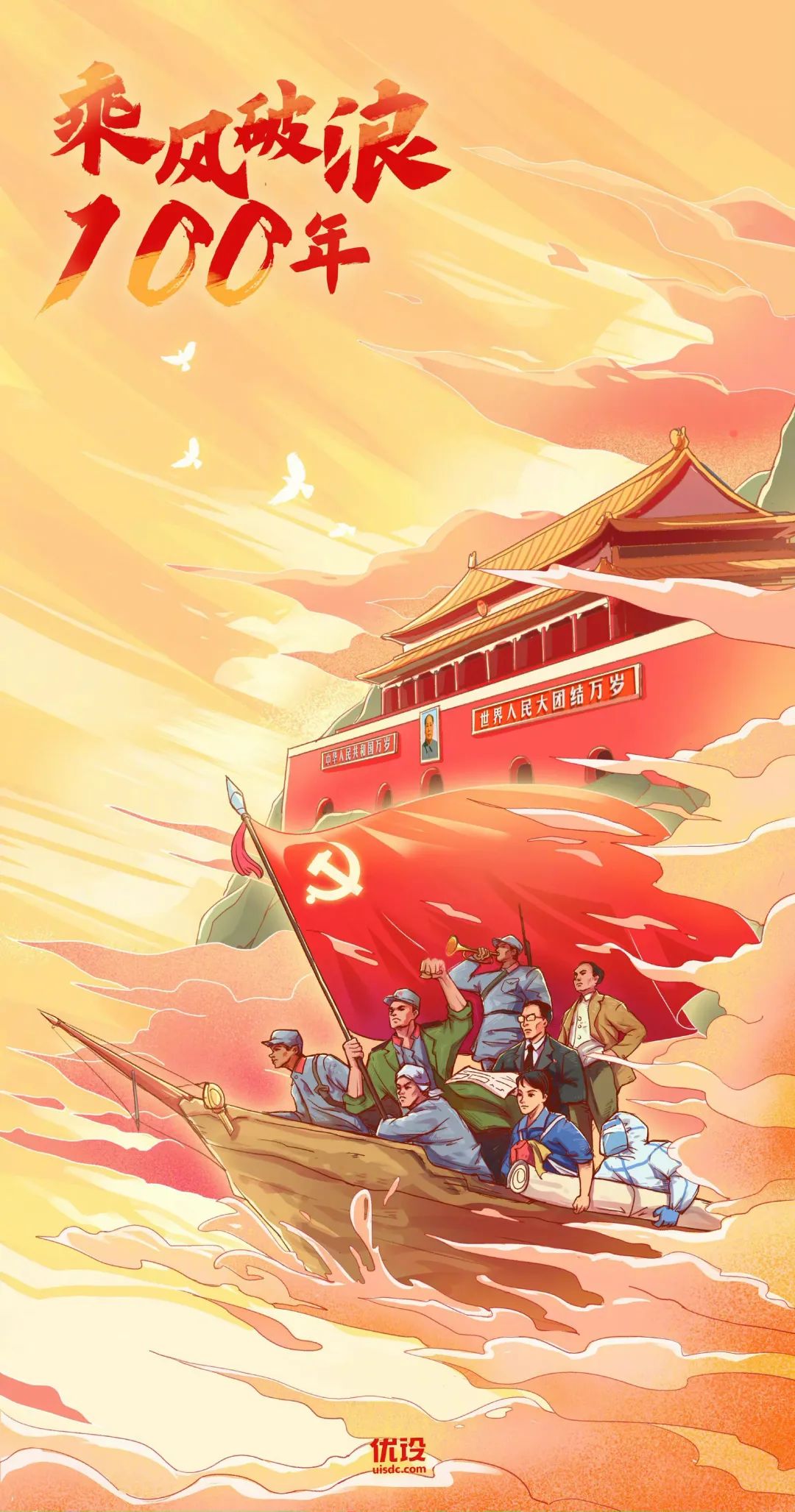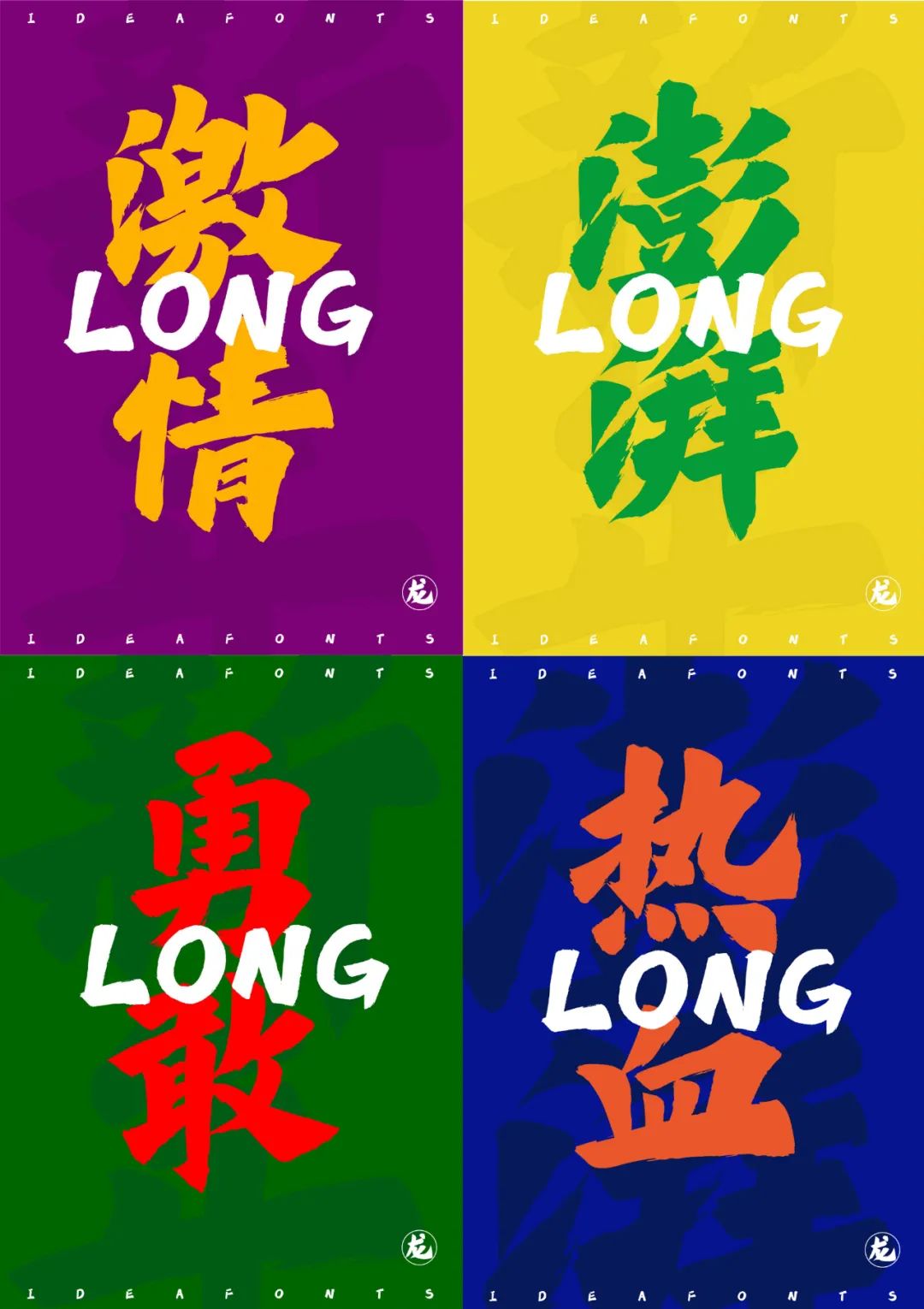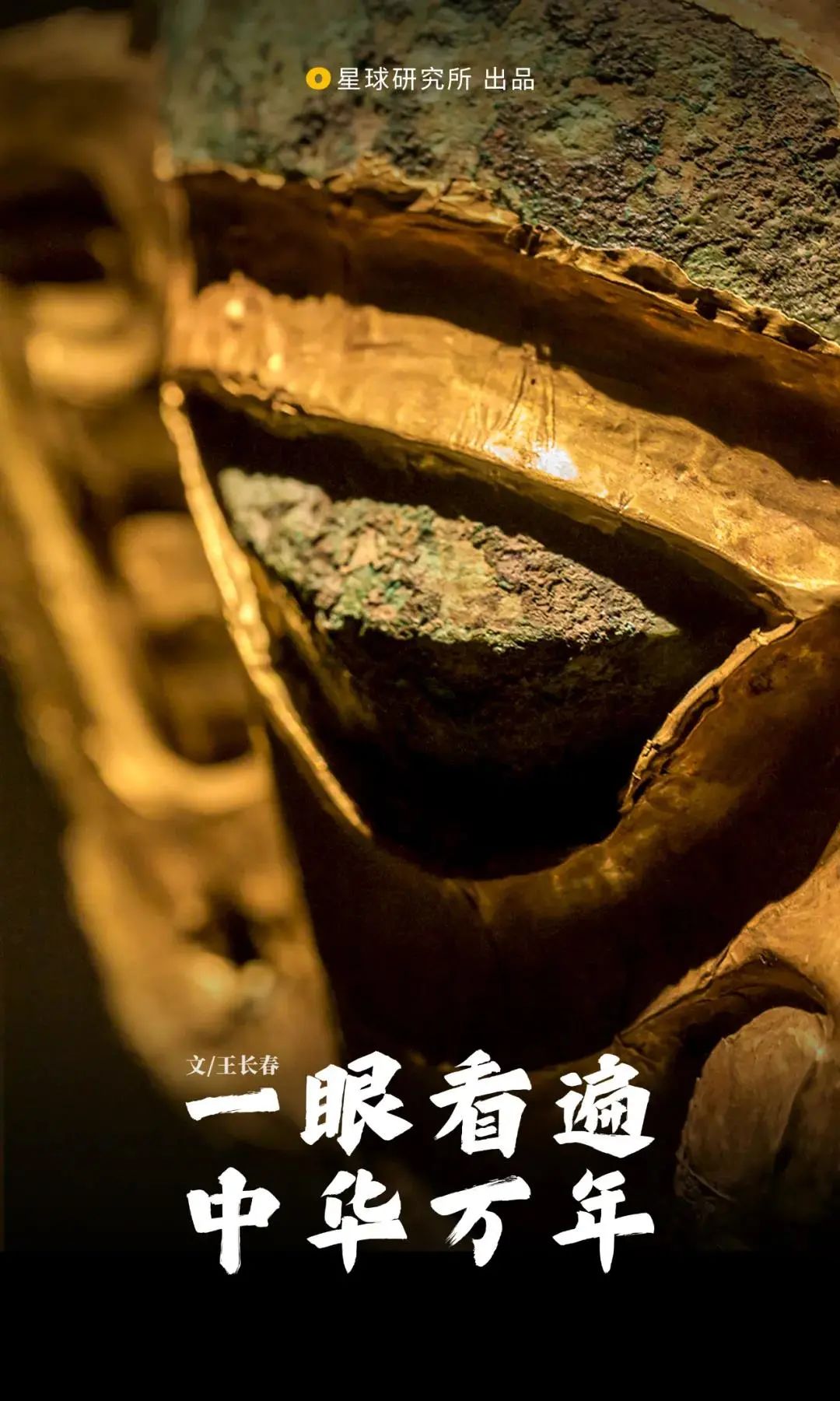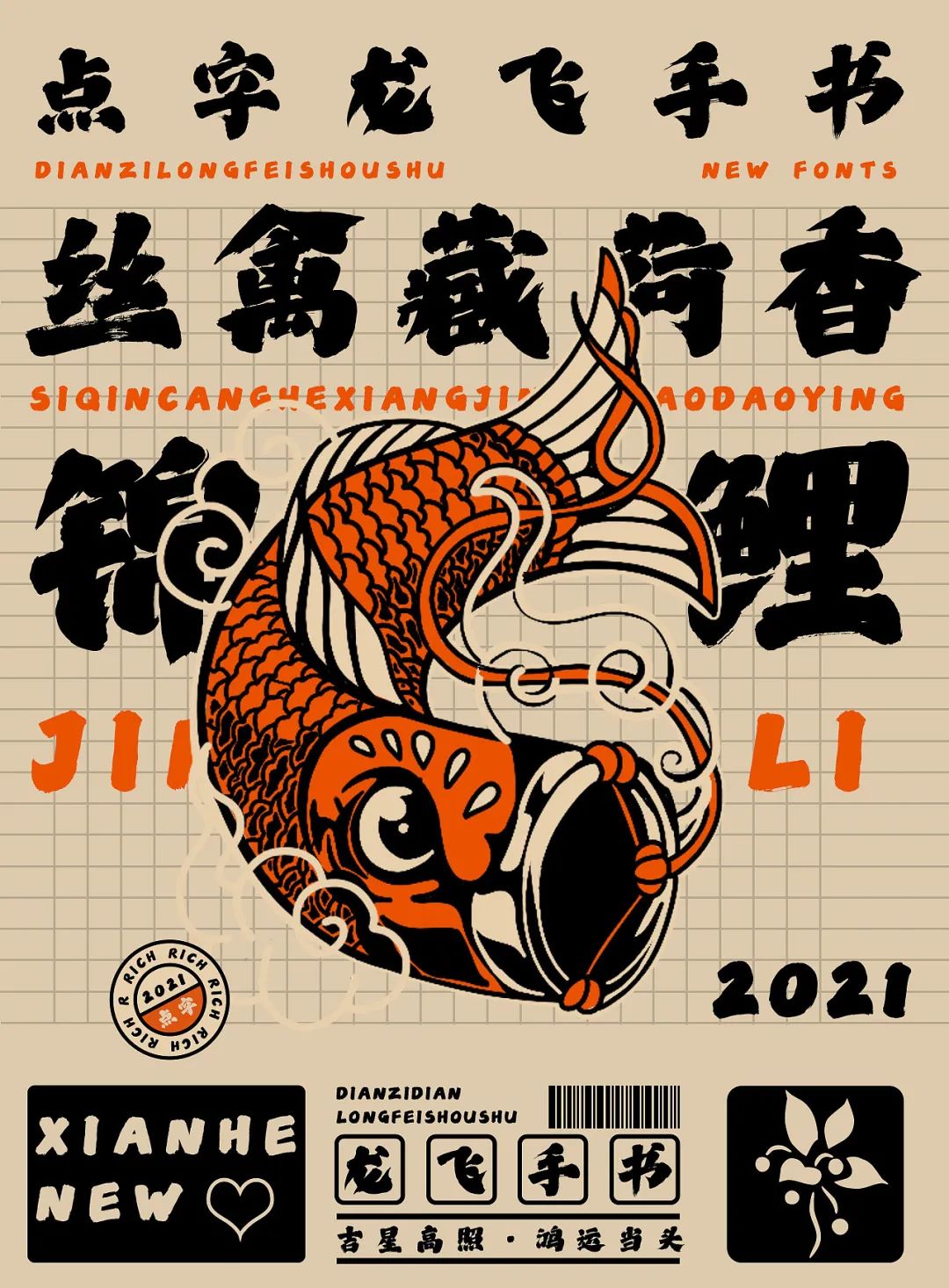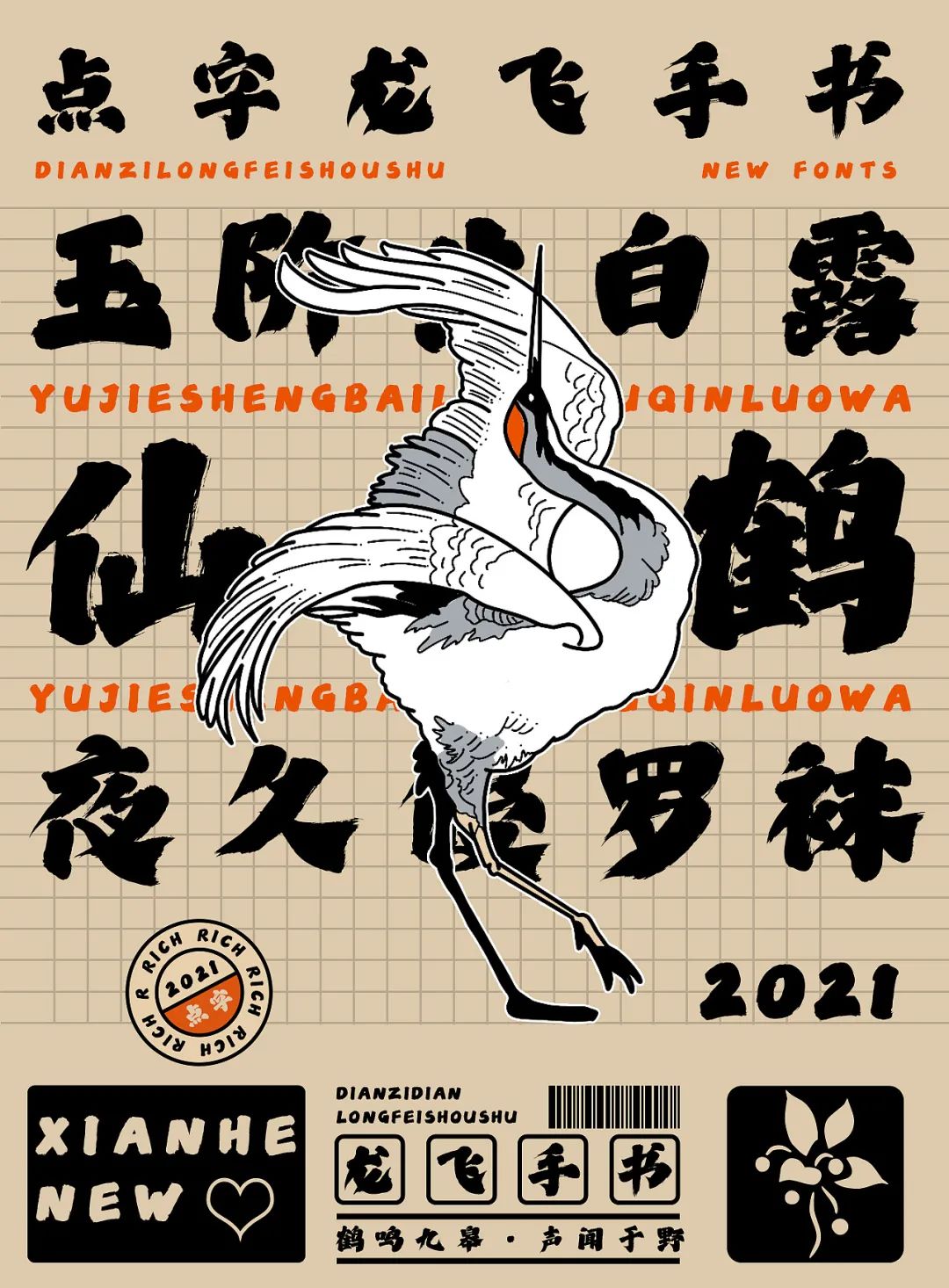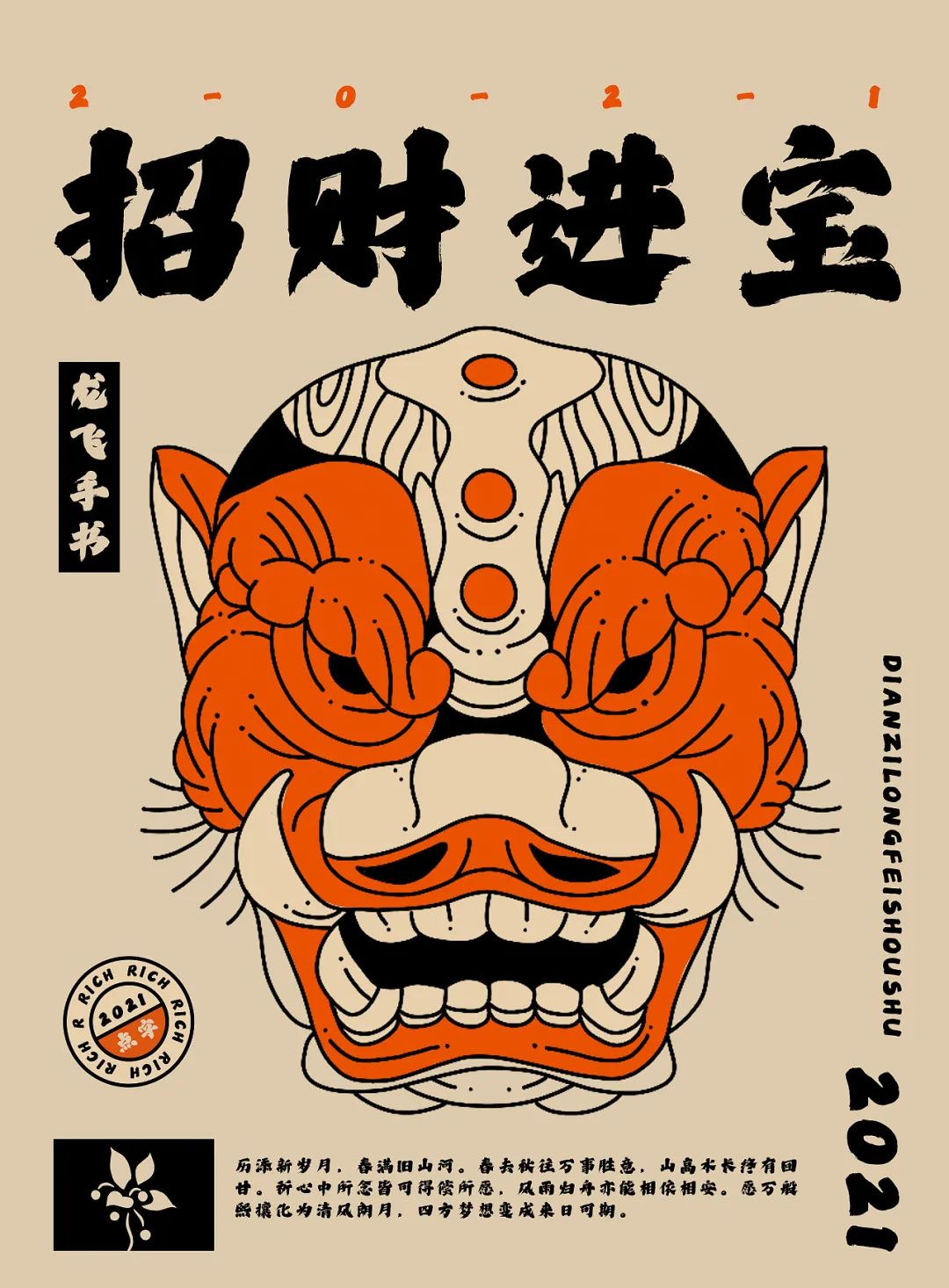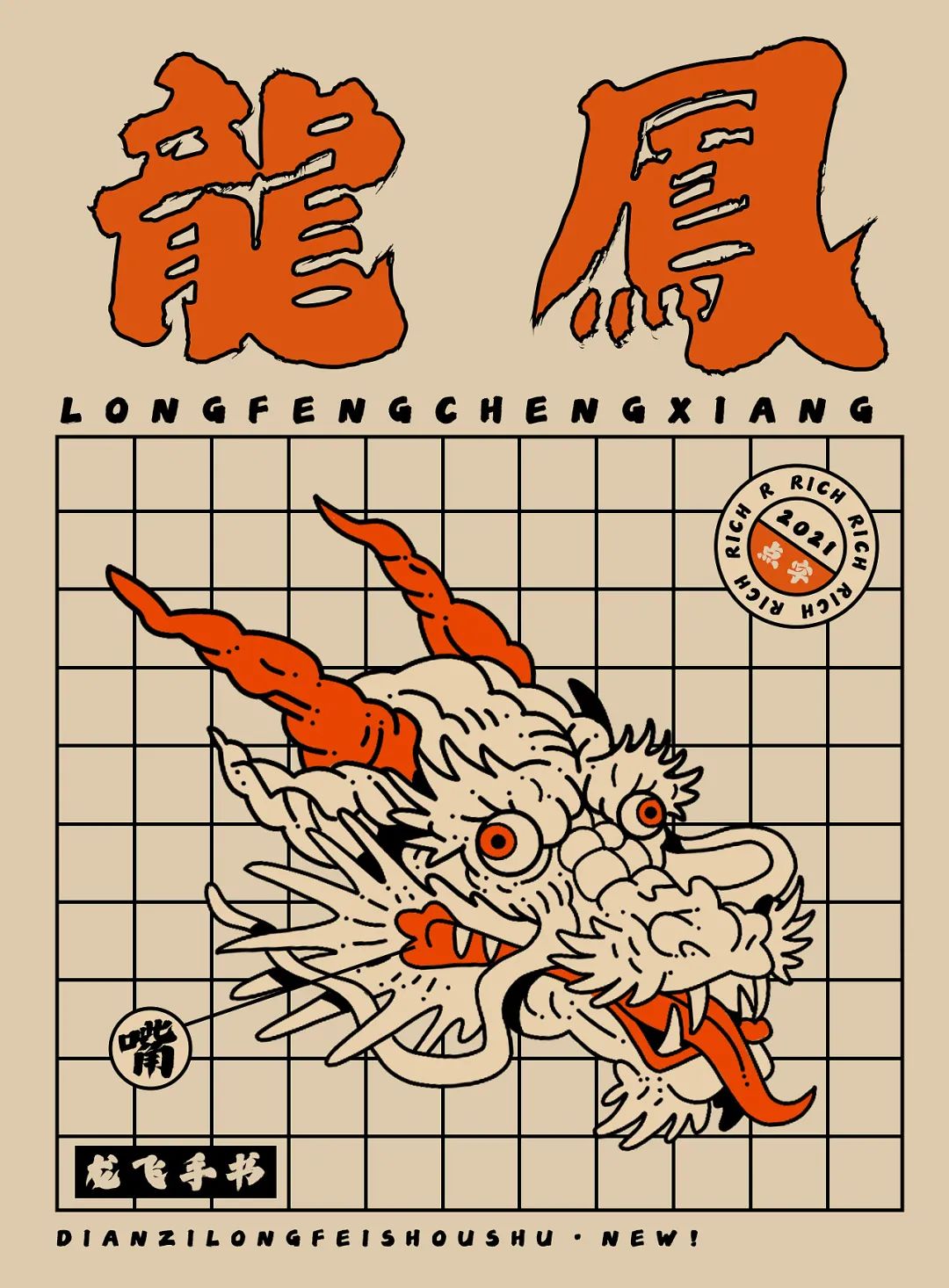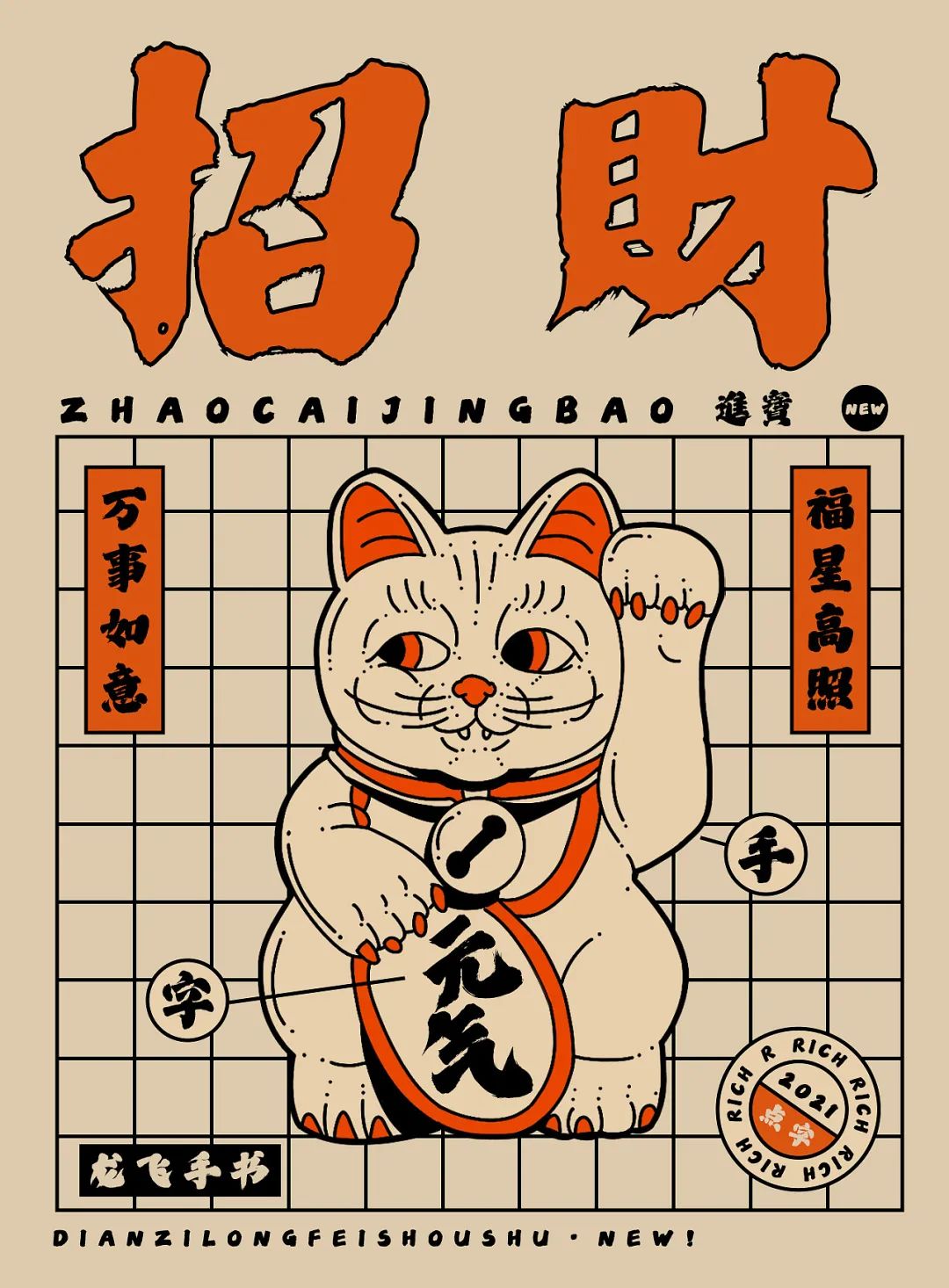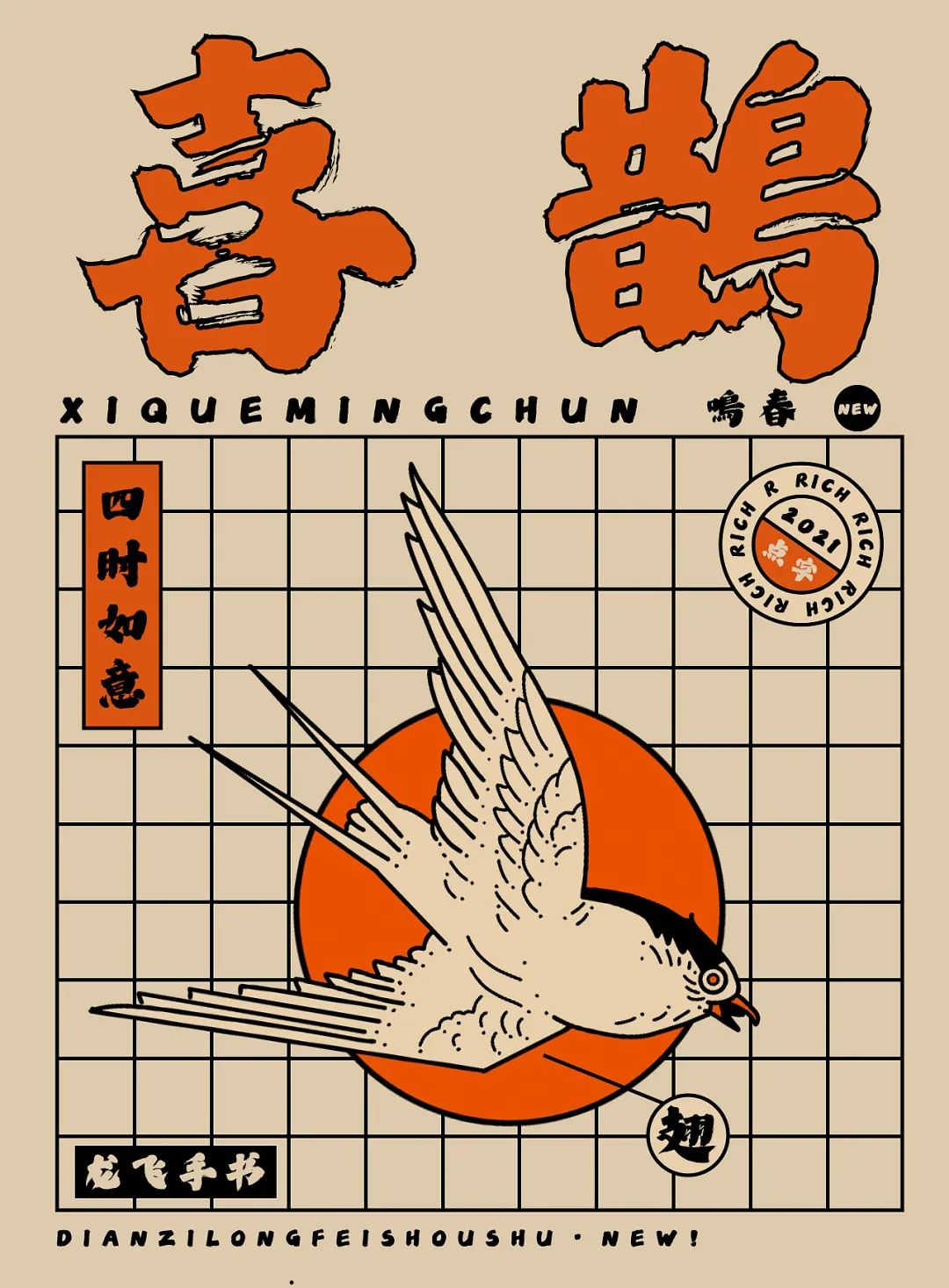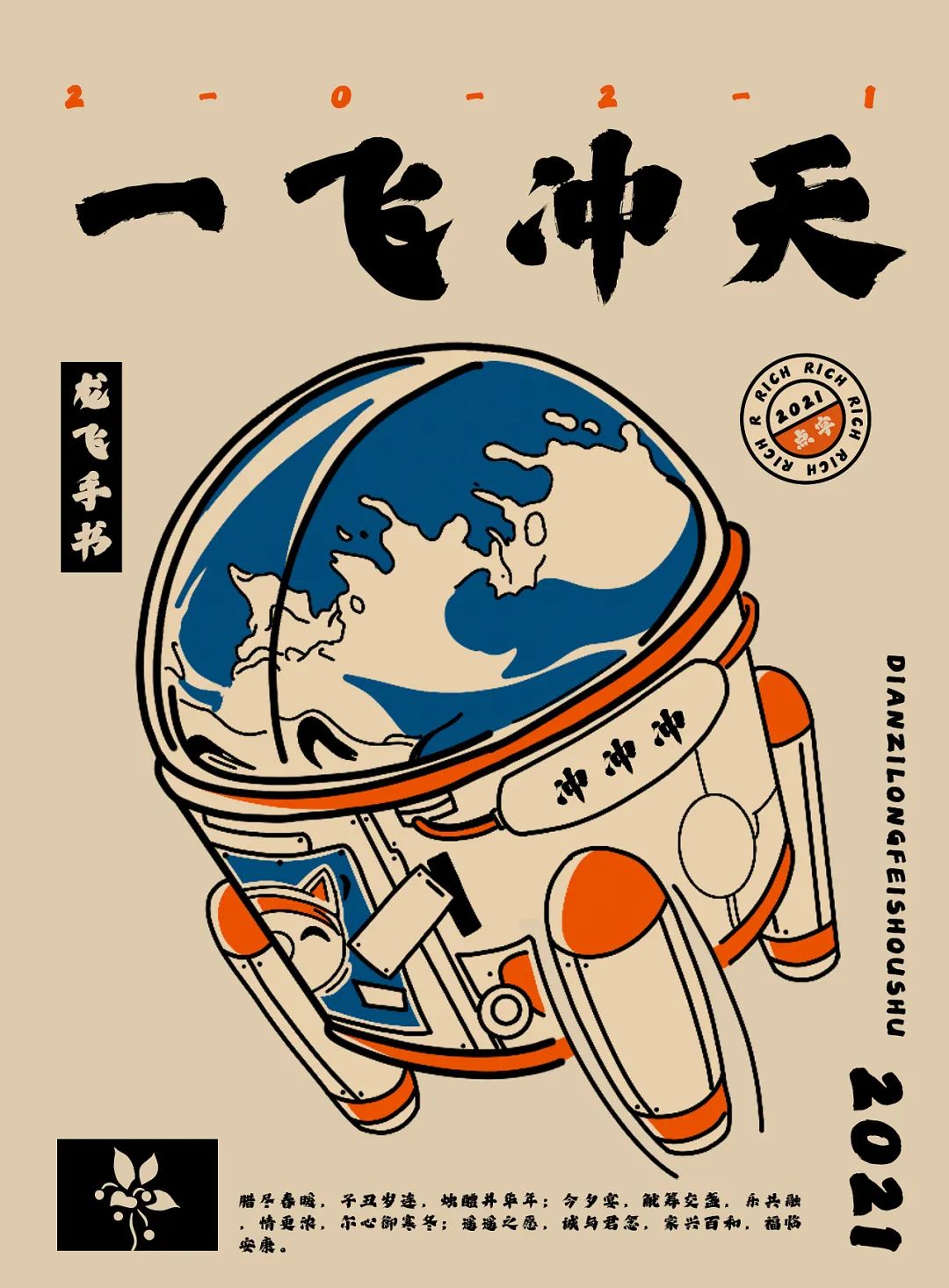
点字龙飞三款字体分享,今天组团出道啦!
三月份上线的热血字体——点字龙飞行楷,相信你一定不陌生!
自发布以来,它的应用次数就快6w了,足见这个字体的好用。
可一款不够用啊,这不二弟——点字龙飞手书也帅帅地登场了!
跟大哥的正统范不一样,点字龙飞手书看起来更开朗豁达,灵感来源于唐朝楷书作品,放大其丰腴敦厚的造型,辅以灵动巧妙的笔触,飞白自然,独具一格。
嗯都挺鲨人的,只是少了点痞帅,别急啊,还有狂躁的三弟,一笔一画都像在挥洒自己的个性,极具辨识度。